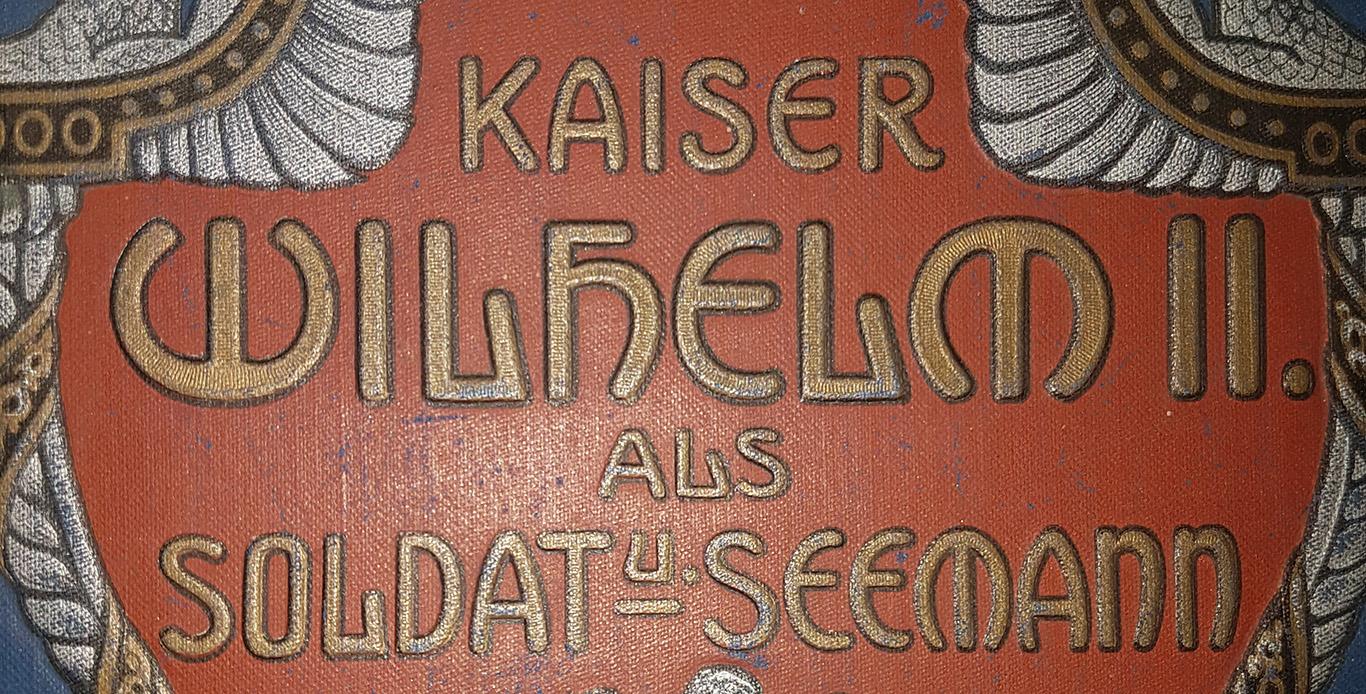
Suche Schrift von diesem Buchcover (Kaiser Wilhelm II. als Soldat und Seemann)
Frage an die Profis, könntet ihr mir vielleicht bitte weiterhelfen. Ich suche diese Schriftart vom folgendem Cover.
Titel:Kaiser Wilhelm II. als Soldat und Seemann.
Erschienen:1902
Das ist Handarbeit. Du wirst allerhöchstens halbwegs ähnliche finden.